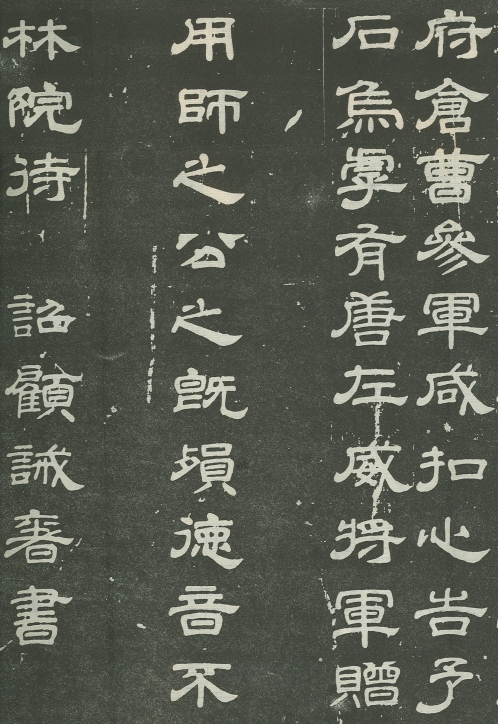
顾诫奢
顾诫奢简介
明皇时人。天宝十五年见任太子率更丞,上元年间为太子文学。工八分,有“顾八分”之目。尝书《吕諲庙碑》、《吕諲碑》等。1984年西安高楼村出土的《高元珪墓誌》,隶书丰茂精劲,不在韩择木之下,篆盖“大唐故左威卫将军赠陈留郡太守高府君墓誌铭》二十字,作玉箸篆,圆健丰茂,有胜于史惟则 ,若其亦出于顾诫奢,又当为篆书新体之一始作俑者。北宋书法家、书学理论家黄伯思《东观餘论》亦有“观其遗迹(指《吕諲碑》),乃知子美(杜甫)弗虚称之。记碑首倒薤,亦自奇古,不独八分可赏”云。
与杜甫订交,杜甫对其推崇之极,作《醉歌行赠公安颜十少府请顾八题壁》中有: “君不见东吴顾文学,君不见西汉杜陵老,诗家笔势君不嫌,词翰升堂为君扫。”再有《送顾八分文学适洪吉州》诗:
中郎石经后,八分盖憔悴。顾侯运炉锤,笔力破馀地。
昔在开元中,韩蔡同赑屃。玄宗妙其书,是以数子至。
御札早流传,揄扬非造次。三人并入直,恩泽各不二。
顾于韩蔡内,辨眼工小字。分日示诸王,钩深法更秘。
文学与我游,萧疏外声利。追随二十载,浩荡长安醉。
高歌卿相宅,文翰飞省寺。视我扬马间,白首不相弃。
骅骝入穷巷,必脱黄金辔。一论朋友难,迟暮敢失坠。
古来事反覆,相见横涕泗。向者玉珂人,谁是青云器。
才尽伤形体,病渴污官位。故旧独依然,时危话颠踬。
我甘多病老,子负忧世志。胡为困衣食,颜色少称遂。
远作辛苦行,顺从众多意。舟楫无根蒂,蛟鼍好为祟。
况兼水贼繁,特戒风飙驶。崩腾戎马际,往往杀长吏。
子干东诸侯,劝勉防纵恣。邦以民为本,鱼饥费香饵。
请哀疮痍深,告诉皇华使。使臣精所择,进德知历试。
恻隐诛求情,固应贤愚异。列士恶苟得,俊杰思自致。
赠子猛虎行,出郊载酸鼻。
《高元珪墓誌》 天宝十五年(756年)